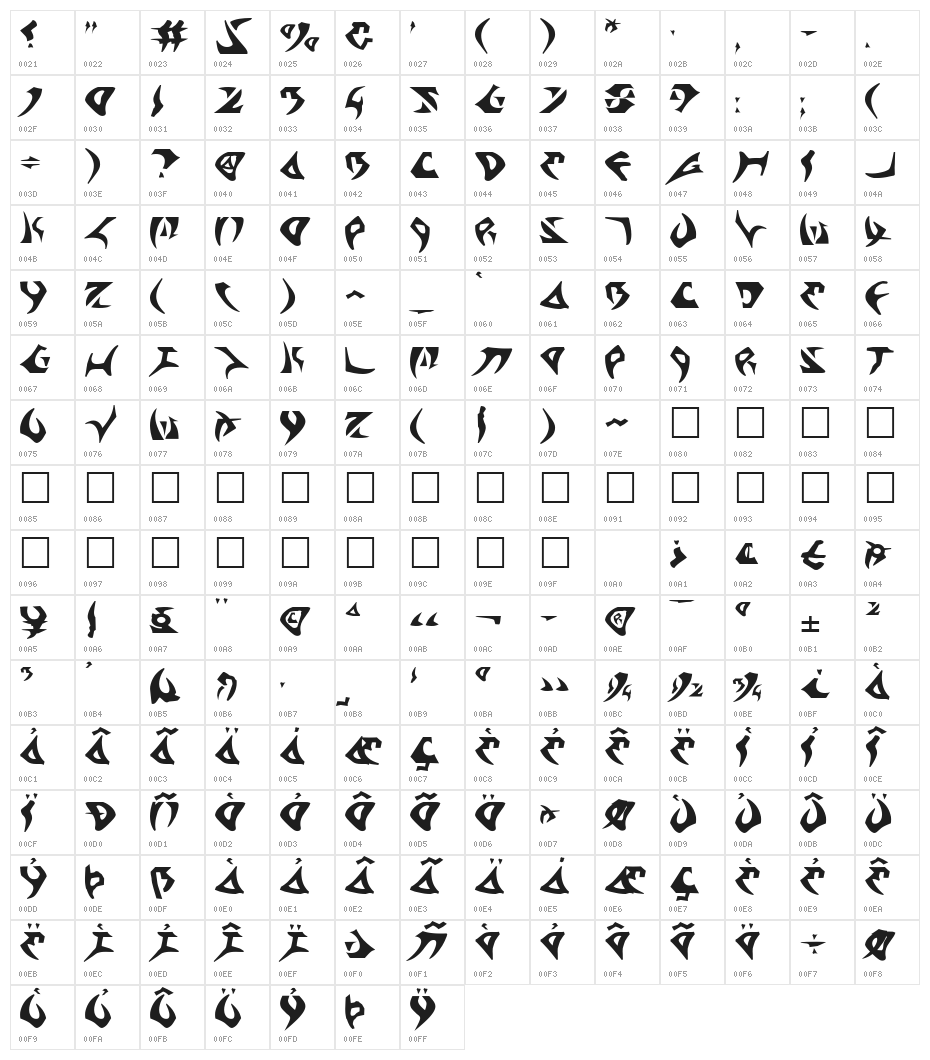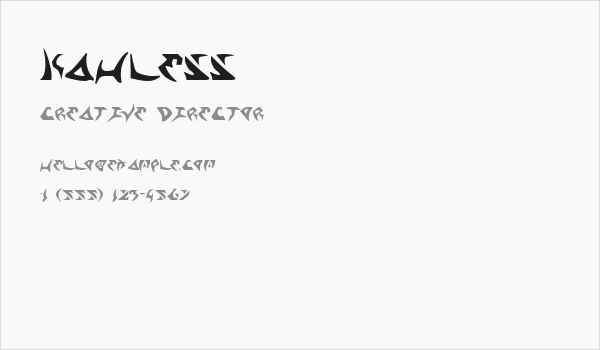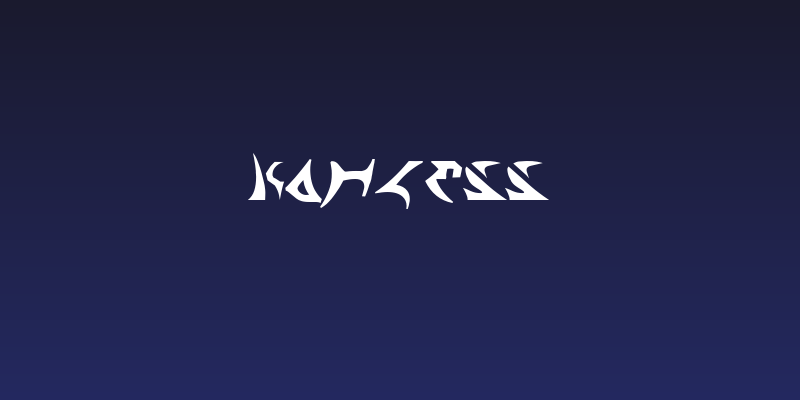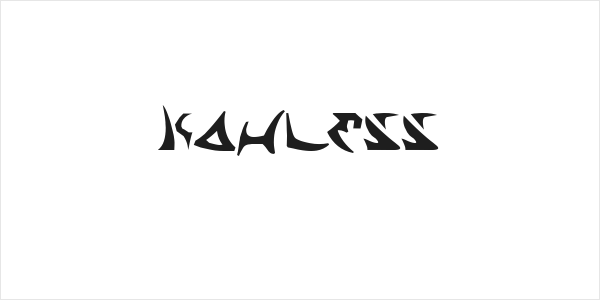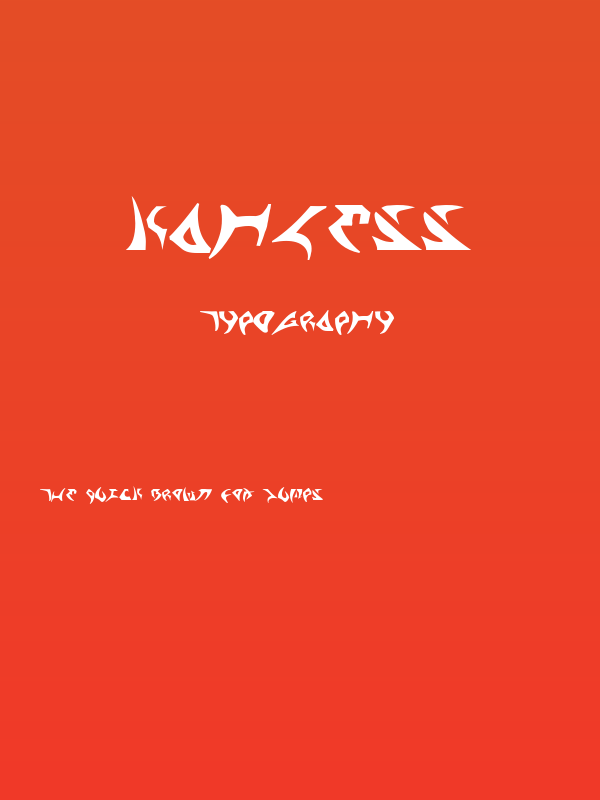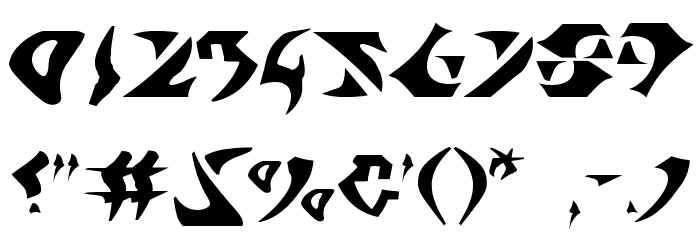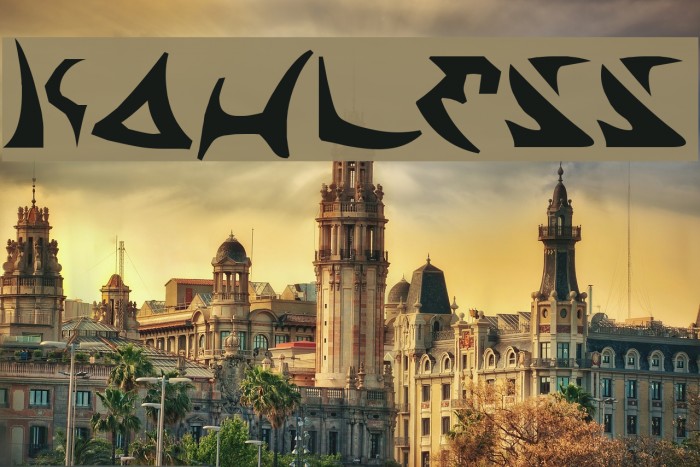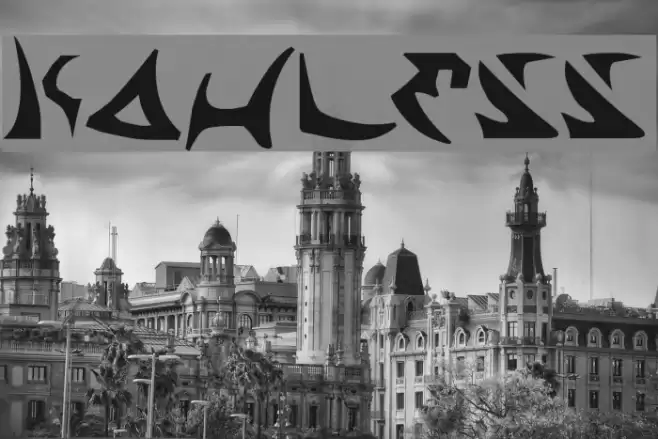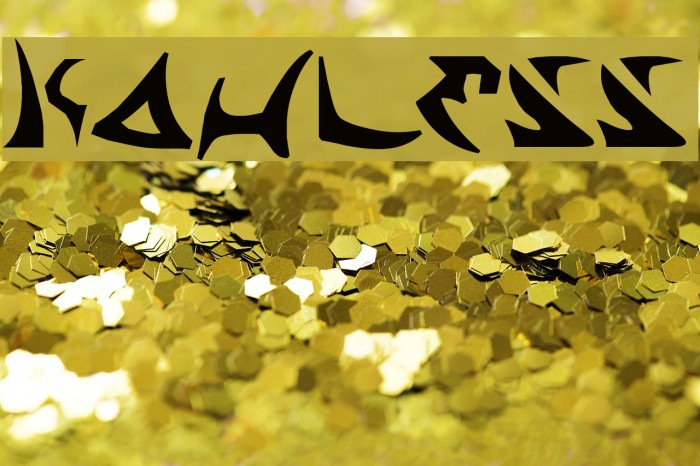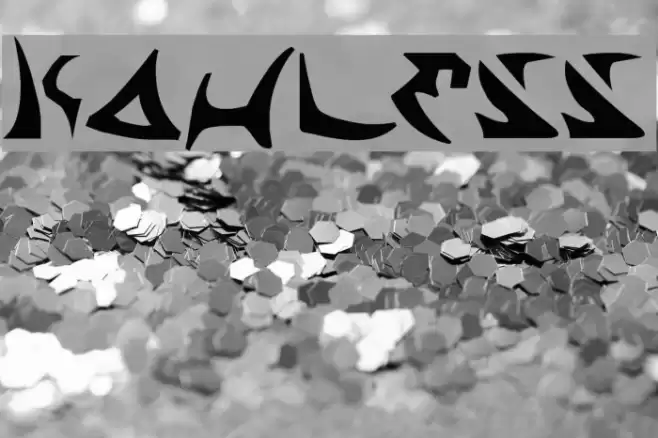
Kahless Font
| Estilo general | Futuristic, Aggressive |
| Proyectos propuestos | Ideal for sci-fi themed designs, video game titles, movie posters, and branding for tech companies. |